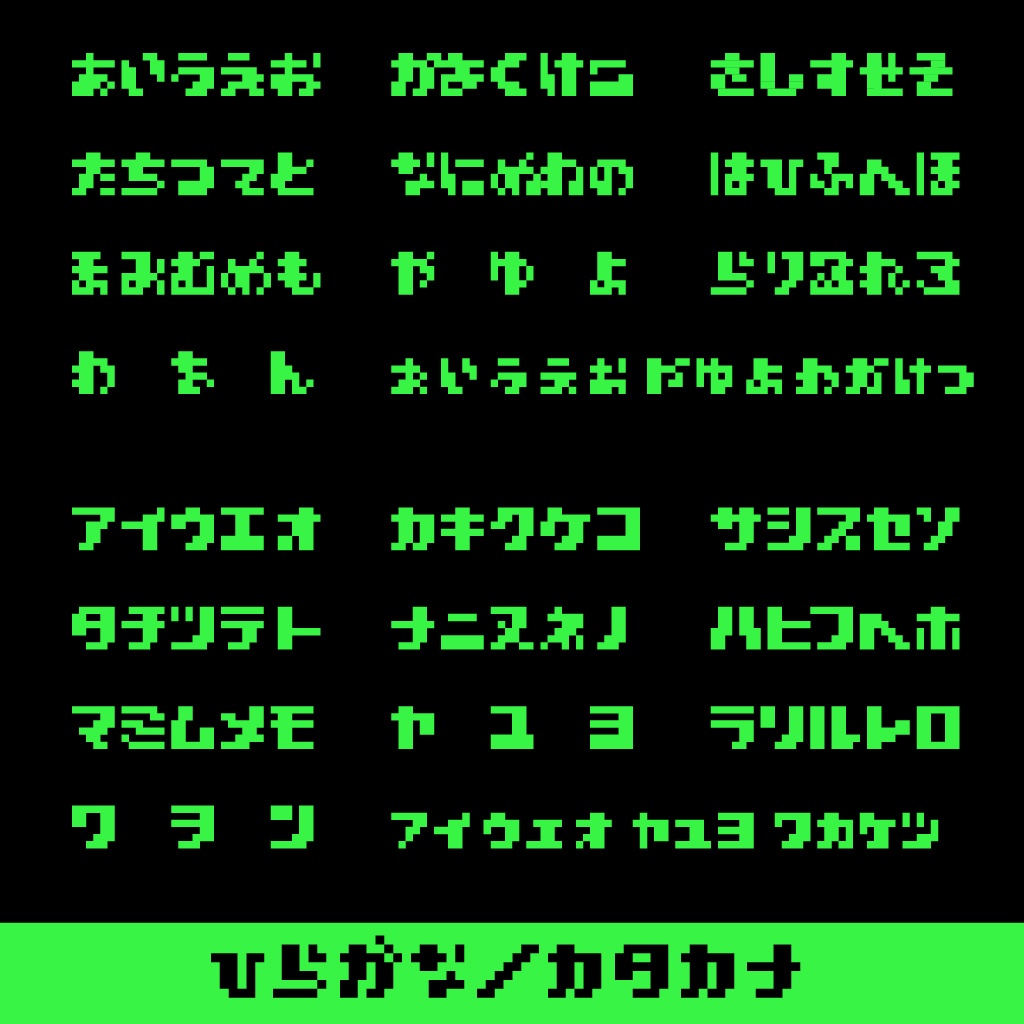
フリーフォント「どっとじ」
レトロゲームを思わせるドット調のフリーフォントになります。 ひらがな・カタカナ・アルファベット全角大文字小文字,半角小文字,一部記号に対応しています。 大文字で使用することを推奨いたします。半角の大文字は対応していません。漢字も非対応です。 (アルファベットの全角などはキー入力後、F9変換で簡単に変換できます) ドット絵orデザインに使いやすいフォントになっています。 「無料ダウンロード」と「投げ銭」でデータの違いはありません。 ご支援いただける方のみ「投げ銭」からダウンロードお願いいたします。 ※公の場で使用し、何かしらの不利益を被ることがあっても当方は責任を負いかねます。ご理解頂けた方のみ、自己責任でご使用ください。 ※個人・商用利用等お好きに使っていただいてかまいません。 ※商標登録する、作者を偽る、フォントデータ自体を二次配布または販売や転売する改変する行為は禁止です。 ※誤動作・誤出力などフォント使用に伴ういかなる問題も、当方は責任を負わないものとします。